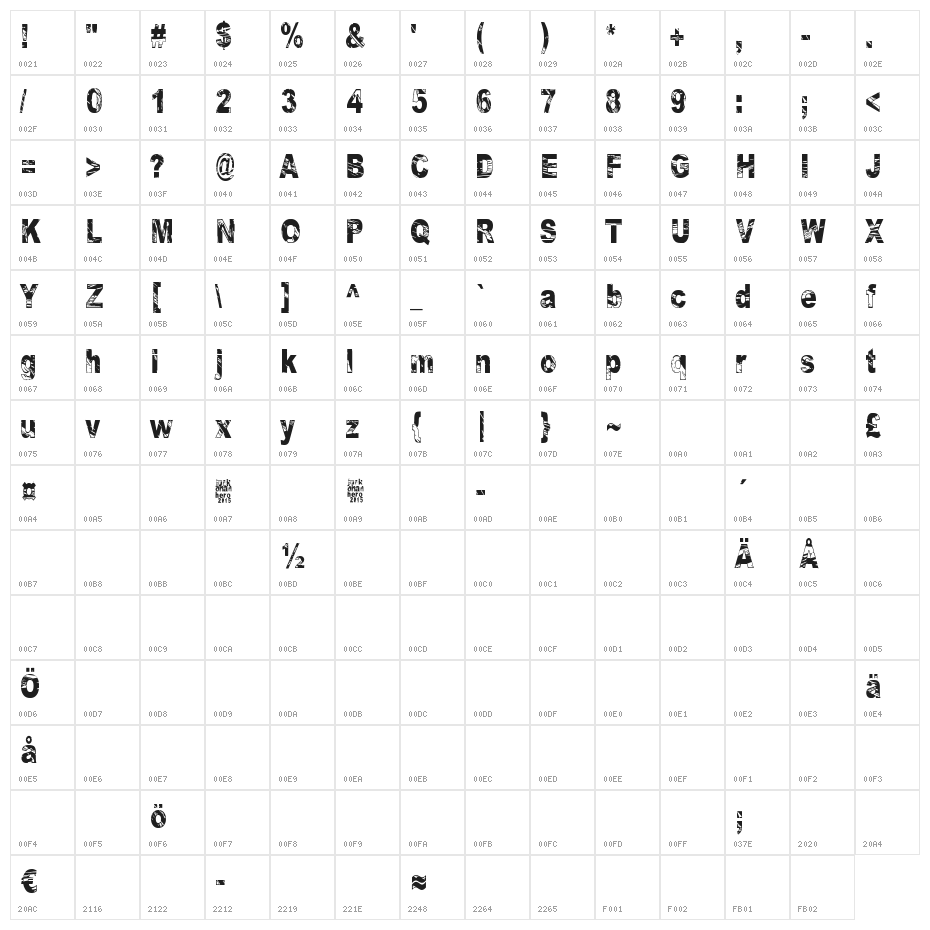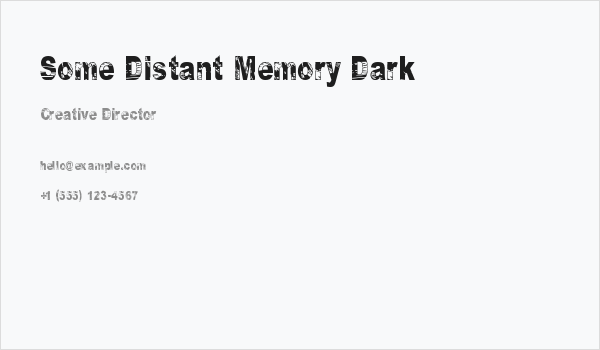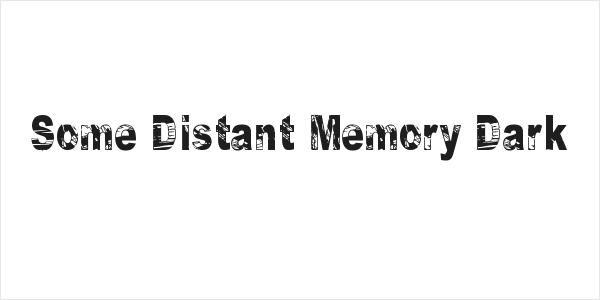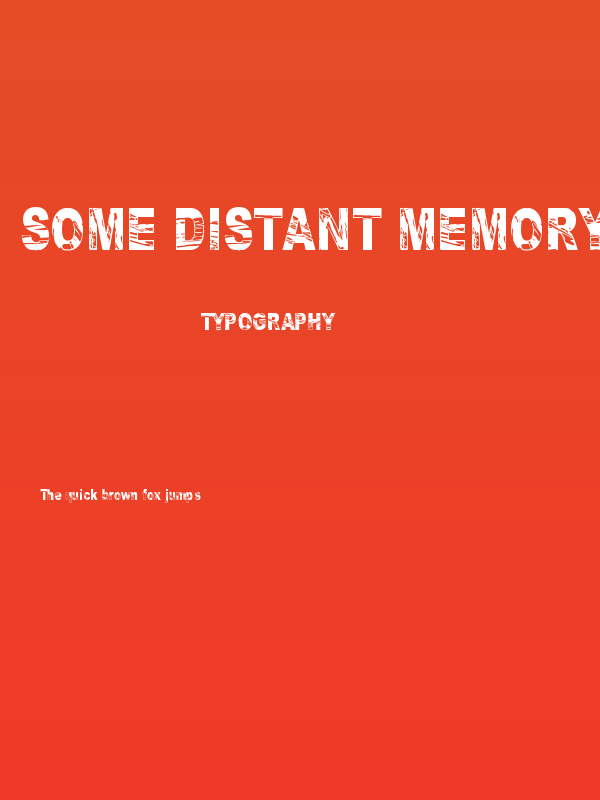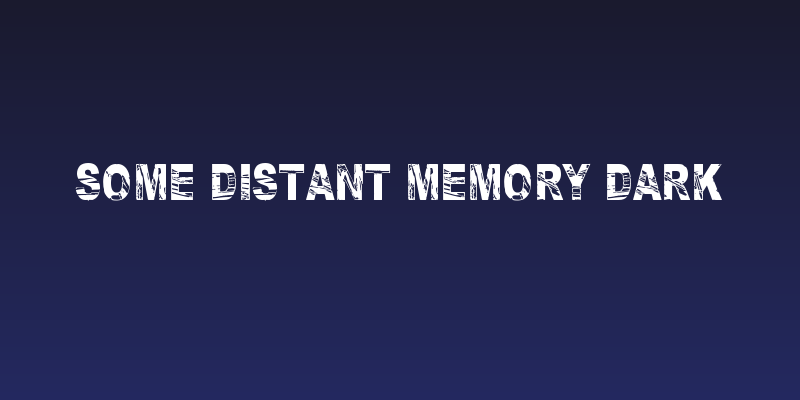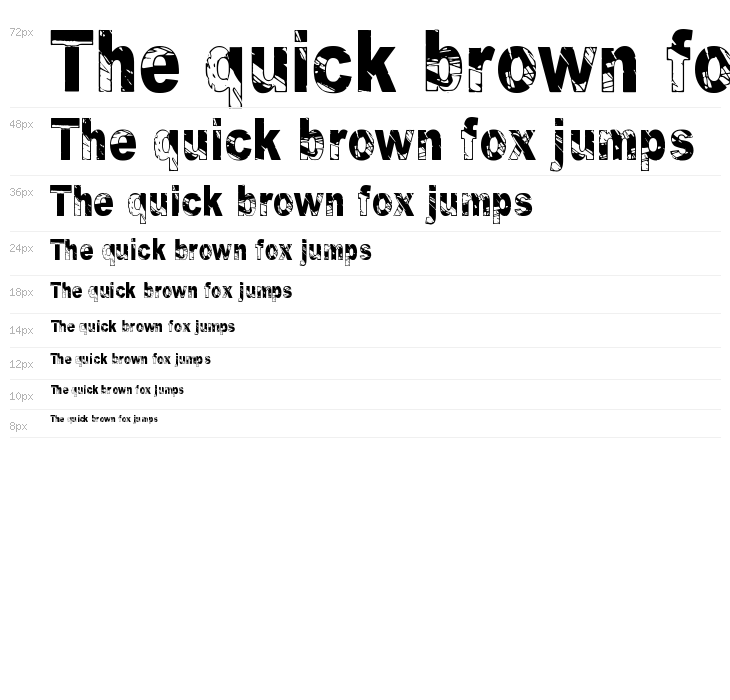
Some Distant Memory Dark Font
| Gesamtstil | Modern, Artistic |
| Vorgeschlagene Projekte | Ideal for album covers, posters, branding for edgy products, or any design needing a bold, artistic touch. |